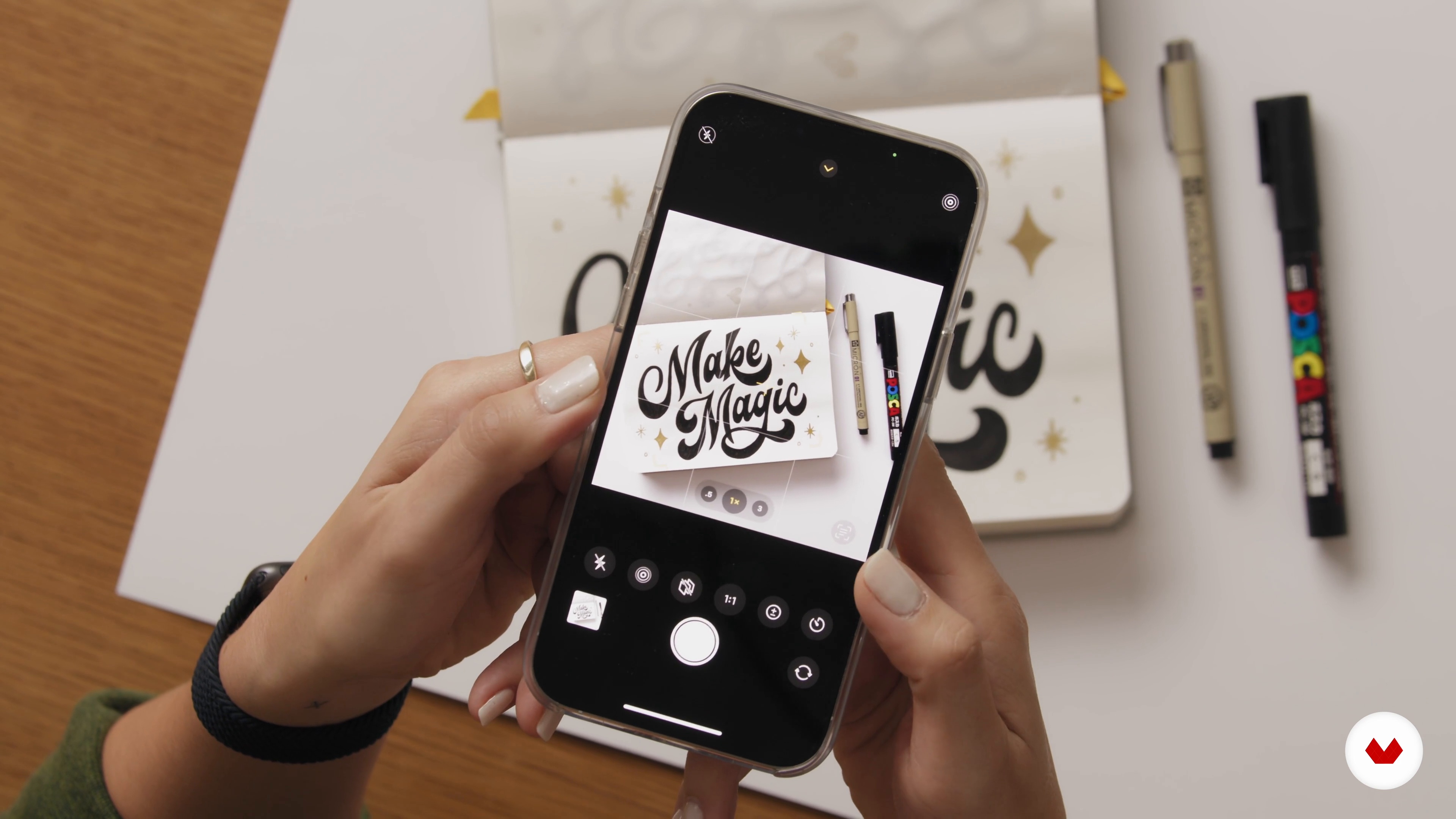
Typografie-Skizzenbuch: Zeichne Buchstaben mit Stil
Ein Kurs von Joanna Muñoz , Illustratorin und Lettering-Künstlerin
“Zum Abschluss dieser Einheit werde ich erklären, wie das Führen eines Skizzenbuchs das Potenzial hat, sich in bezahlte Kundenarbeit zu verwandeln.”
In dieser Videolektion behandelt Joanna Muñoz das Thema: Arbeit teilen, um Arbeit zu bekommen, das Teil dieses Domestika-Onlinekurses ist: Typografie-Skizzenbuch: Zeichne Buchstaben mit Stil. Erforsche die Kunst des Handletterings, indem du ein Skizzenbuch mit typografischen Kompositionen füllst und dabei eine Vielzahl kreativer Techniken anwendest.
“Arbeit teilen, um Arbeit zu bekommen In dieser Lektion zeige ich Ihnen, wie ich meine Arbeit in sozialen Medien teile. Zuerst öffne ich meine Kamera im Fotomodus. Hier habe ich meine Skizze angelegt. Ich habe die Stifte, mit denen ich die Skizze erstellt habe, was ihm ein bisschen Kontext gibt. Ich habe ein weißes Blatt Papier, um ihm einen schönen neutralen Hintergrund zu geben damit mein Schriftzug auffällt. Ich werde mein Telefon über meiner Skizze positionieren, und ändern Sie das Verhältnis so, dass es ein quadratisches Foto ist. Ich werde dafür sorgen, dass mein Schriftzug das Highlig...”
Zusammenfassung des Kurses: Typografie-Skizzenbuch: Zeichne Buchstaben mit Stil
Joanna Muñoz ist Lettering-Künstlerin und Illustratorin und lebt in Los Angeles, USA. Sie ist die Künstlerin hinter dem Studio Wink & Wonder. Ihre Arbeiten sind eine humorvolle Mischung aus ungewöhnlichen Buchstabenformen, Regenbogenfarben und positiven Botschaften. Obwohl sie zunächst Informatik und später Grafikdesign studierte, fand sie schließlich ihre Nische im Handlettering. Heute teilt sie ihre Arbeit mit 42.000 Followern auf Instagram.
Sie hat individuelle Letterings für Marken wie HBO, Nickelodeon, Pottery Barn, Michael Kors, Microsoft und PayPal sowie für kleine, lokale Unternehmen entworfen. Daneben veranstaltet sie Lettering-Events und gibt Workshops in Südkalifornien. Ihr Ziel ist es, Kunst zu schaffen, die Menschen anspricht und sie dazu ermutigt, ihr Leben authentisch und nach ihren eigenen Vorstellungen zu gestalten.